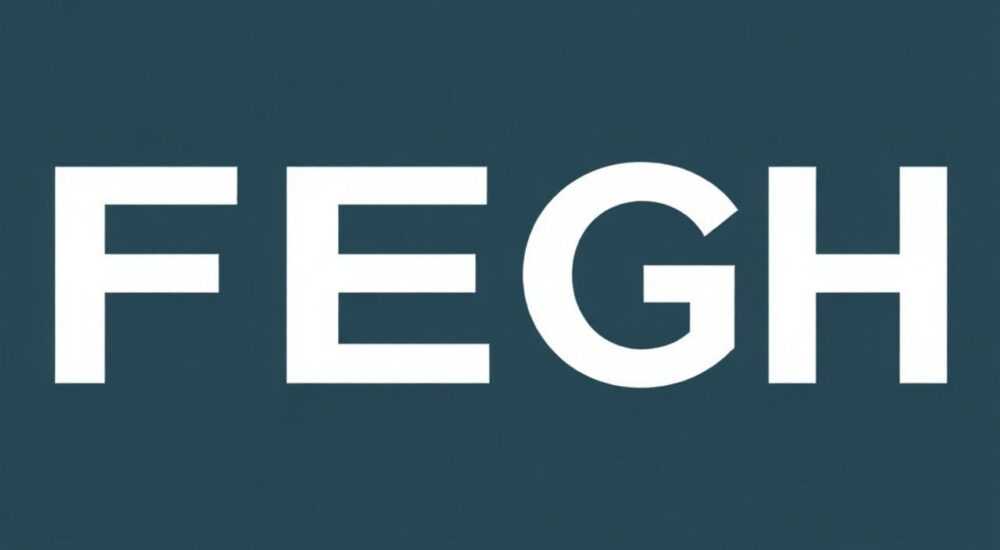
Как сделать жирный шрифт в figma
Как сделать жирный шрифт в Figma — это базовая, но критически важная задача для любого дизайнера, работающего с интерфейсами. Неправильное применение жирности может нарушить иерархию, снизить читаемость и испортить визуальную согласованность продукта. Даже небольшая ошибка в выборе веса шрифта — например, замена Bold на SemiBold — может привести к тому, что текст станет менее заметным на мобильном экране или потеряется визуальный акцент в кнопке. Умение точно управлять весом шрифта — не просто технический навык, а ключевой элемент профессионального дизайна.
Почему правильная жирность шрифта имеет значение
Жирность шрифта — это не просто эстетический выбор. Она напрямую влияет на восприятие информации, визуальную иерархию и даже скорость чтения. Исследования Nielsen Norman Group показывают, что пользователи сканируют интерфейсы за 2–3 секунды, и жирный текст становится первым ориентиром, который привлекает внимание. Неправильно подобранная жирность может превратить важный призыв к действию в незаметный элемент, а заголовок — в визуальный шум.
Представьте, что вы проектируете интерфейс мобильного банка. Заголовок «Ваш баланс: 15 000 ₽» должен быть легко читаем даже при беглом взгляде. Если вы используете Regular вместо Bold, пользователь может пропустить эту информацию — особенно в условиях плохого освещения или на маленьком экране. В то же время, если вы сделаете жирным каждый элемент, иерархия исчезнет, и интерфейс станет перегруженным.
Кроме того, не все шрифты имеют одинаковые варианты веса. Некоторые бесплатные шрифты из Google Fonts или встроенные в Figma могут не содержать Bold, а только SemiBold или Medium. В таких случаях Figma применяет алгоритмическую жирность — искусственное утолщение контуров. Это не то же самое, что настоящий жирный вариант, разработанный типографом. Качество текста падает: буквы становятся толще, но теряют пропорции, а в мелком размере — начинают слипаться.
Как сделать жирный шрифт в Figma: пошаговая инструкция
Процесс изменения веса шрифта в Figma прост, но требует внимания к деталям. Вот пошаговая инструкция:
- Выберите текстовый слой на холсте. Можно щелкнуть по тексту или выделить его в панели Layers.
- Откройте панель свойств справа — она автоматически отобразит параметры текста.
- Найдите поле «Weight». Оно находится рядом с размером шрифта («Size») и именем шрифта («Font»).
- Щелкните по текущему значению (например, «Regular»). Появится выпадающий список с доступными весами.
- Выберите «Bold» (700). Если нужен более тяжёлый вариант — выберите «Extra Bold» (800) или «Black» (900).
- Если «Bold» не отображается — проверьте, поддерживает ли выбранный шрифт этот вес. Некоторые шрифты имеют только Regular и Italic.
Если вы работаете с группой текстовых элементов, выделите их все одновременно — изменения применятся ко всем сразу. Это особенно полезно при редактировании списков, заголовков или карточек.
Что такое вес шрифта и как его выбрать
Вес шрифта — это числовое значение, обозначающее толщину линий букв. Стандартная шкала от 100 до 900, где каждые 100 единиц — это новый уровень жирности. Вот как они соответствуют названиям:
Числовое значение |
Название в Figma |
Применение |
100 |
Thin |
Декоративные заголовки, минимализм |
200 |
Extra Light |
Подзаголовки, вторичный текст |
300 |
Light |
Текст в светлых интерфейсах |
400 |
Regular |
Основной текст, тело документа |
500 |
Medium |
Слабый акцент, кнопки, метки |
600 |
Semi Bold |
Заголовки H2–H3, важные элементы |
700 |
Bold |
Заголовки H1, призывы к действию |
800 |
Extra Bold |
Печать, логотипы, экстремальный акцент |
900 |
Black |
Редко, только для больших размеров |
Не существует универсального правила «всегда использовать Bold». Например, в интерфейсах для пожилых пользователей может быть предпочтительнее SemiBold (600), потому что Bold (700) может казаться слишком агрессивным. В современных материальных дизайнах (Material Design 3) рекомендуется использовать Medium (500) для заголовков, а Bold — только для акцентов.
Частые ошибки при применении жирности и как их избежать
Даже опытные дизайнеры допускают ошибки, связанные с жирностью. Вот самые распространённые:
- Использование искусственной жирности. Если шрифт не имеет Bold-варианта, Figma создаёт его алгоритмически. Результат — размытые, нечёткие буквы, особенно в размерах меньше 14px. Решение: всегда проверяйте, есть ли в списке шрифта Bold. Если нет — замените шрифт на аналог с полной поддержкой весов (например, Inter, Roboto, Lato).
- Переиспользование Bold везде. Если каждый заголовок, кнопка и метка сделаны жирными, ничего не выделяется. Решение: используйте иерархию: Regular → Medium → SemiBold → Bold. Оставьте Bold только для самого важного.
- Несогласованность между платформами. На iOS Bold может выглядеть иначе, чем на Android. Решение: тестируйте дизайн на реальных устройствах или используйте компоненты с фиксированными весами, а не настройками по умолчанию.
- Игнорирование доступности. Слишком жирный текст на светлом фоне может вызывать усталость глаз. Решение: соблюдайте контрастность (минимум 4.5:1 для текста 16px и меньше по WCAG).
Чтобы избежать этих ошибок, создайте в Figma собственную систему стилей текста. Используйте Text Styles — это позволит вам применять одинаковые настройки жирности по всему проекту и легко обновлять их в одном месте.
Как работать с шрифтами без жирных вариантов
Иногда вы сталкиваетесь с шрифтами, которые не имеют Bold. Это типично для кастомных или бесплатных шрифтов, скачанных с сайта типа DaFont или Google Fonts. В этом случае Figma автоматически применяет «fake bold» — искусственное утолщение. Но это не лучшее решение.
Что делать?
- Вариант 1: Замените шрифт. Найдите аналог с полной палитрой весов. Например, если вы используете «Open Sans», замените его на «Inter» — он бесплатный, современный и имеет 9 весов.
- Вариант 2: Используйте SemiBold. Если Bold отсутствует, но есть SemiBold — это лучше, чем искусственная жирность. SemiBold (600) часто выглядит естественнее, чем «fake Bold».
- Вариант 3: Увеличьте размер. Вместо жирности увеличьте размер текста на 1–2 пункта. Это может компенсировать недостаток визуального веса без ущерба для качества.
- Вариант 4: Добавьте тень или контур (осторожно). В редких случаях — например, для логотипов — можно использовать очень тонкую тень (1px, прозрачность 10%), чтобы создать эффект объёма. Но это не для основного текста!
Лучшие практики: когда и где использовать жирный шрифт
Правильное применение жирности — это искусство баланса. Вот проверенные практики от ведущих дизайнерских команд:
- Заголовки H1 — всегда Bold (700) или Extra Bold (800). Это основной акцент страницы.
- Заголовки H2–H3 — SemiBold (600). Достаточно для выделения, но не перегружает.
- Кнопки CTA — Bold. Важно, чтобы пользователь мгновенно понял, что это действие.
- Текст в навигации — Regular или Medium. Жирность здесь нарушает спокойствие интерфейса.
- Подписи к изображениям — Regular. Не отвлекайте от основного контента.
- Метки и статусы — SemiBold. Например: «Активно», «Ошибка», «Готово».
Экспертное мнение: как дизайнеры используют жирность в реальных проектах
Мы поговорили с Еленой Михайловой — старшим UX-дизайнером из команды Яндекс.Маркета. Её команда работает с 20+ миллионами пользователей ежедневно.
Елена также подчёркивает важность проверки на разных экранах: «На iPhone 14 Pro Max Bold выглядит идеально, а на iPhone SE — уже перегружает. Мы делаем адаптивные стили: на маленьких экранах SemiBold становится стандартом для заголовков.»
Умение правильно применять жирный шрифт в Figma — это не просто технический навык, а фундаментальный элемент профессионального дизайна интерфейсов. Он влияет на восприятие, удобство, доступность и даже конверсию. Неправильная жирность может разрушить всю работу, даже если макет выглядит красиво. Главное правило: жирность — это инструмент акцента, а не способ сделать текст «круче».
- Жирный шрифт в Figma выбирается через панель свойств — поле «Weight».
- Используйте только настоящие веса шрифта, а не алгоритмическую жирность.
- Создавайте Text Styles для единообразия и быстрого обновления.
- Bold применяется только для акцентов — не более 3 элементов на экране.
- Тестируйте жирность на разных экранах и с учётом доступности.